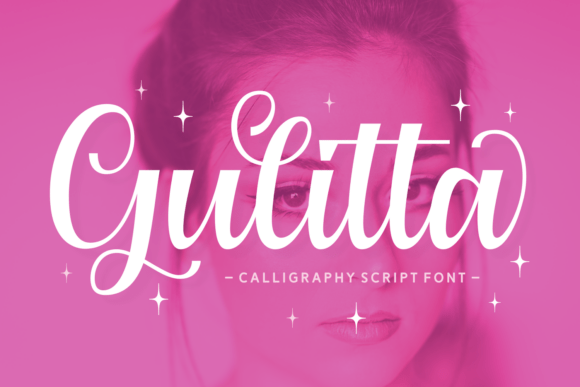
Gulitta
Gulittaのような高品質の素材をお探しの場合、このプレミアムパッケージはクリエイティブなプロジェクトに素晴らしい選択です。
精密に作られたGulittaは、クリーンなベクター、滑らかなタイポグラフィ、そして安心のための商用ライセンスを提供します。
POD(オンデマンド印刷)製品、結婚式の招待状、またはソーシャルメディアのグラフィックを作成している場合でも、Gulittaは理想的です。